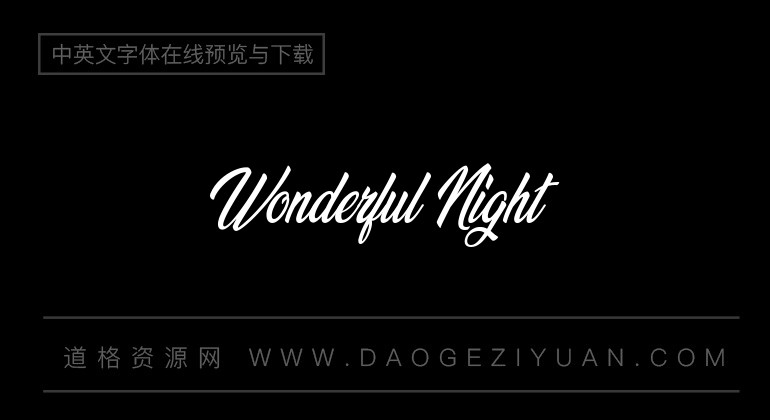
Wonderful Night
Wonderful Night(美好夜晚)是一种华丽而充满活力的手写风格字体。它具有明亮的颜色和明显的表现力,可以让文本看起来更加生动有趣。 该字体的设计师是来自印度的 Rizal Khurasan,它的特点是字母之间相互连接,形成一个流畅的手写效果。它的笔画线条灵活多变,有时圆润,有时锐利。整体来看,Wonderful Night 字体十分适合用于印刷、海报、网页设计和其他短文本应用。
Wonderful Night是一款非常不错的手写艺术字体,具有很好的视觉感,适合于文化类的宣传设计、商业类品牌的广告和产品包装设计以及个性化文字排版等较多场景。